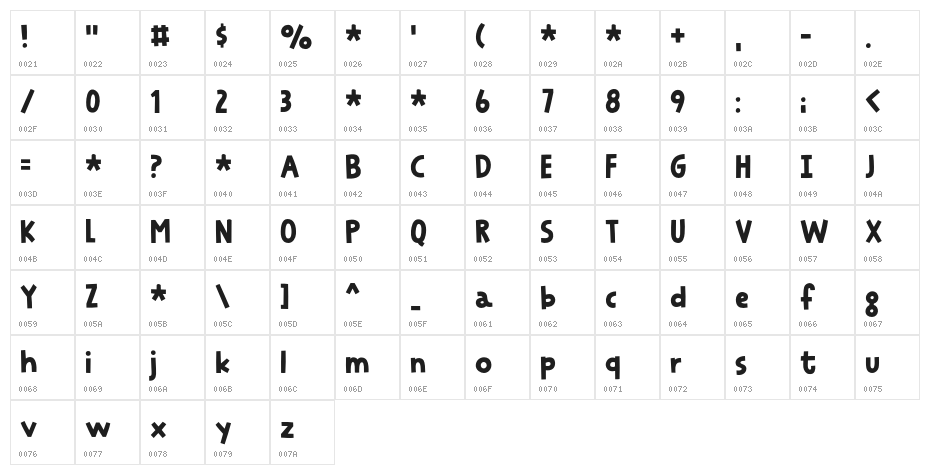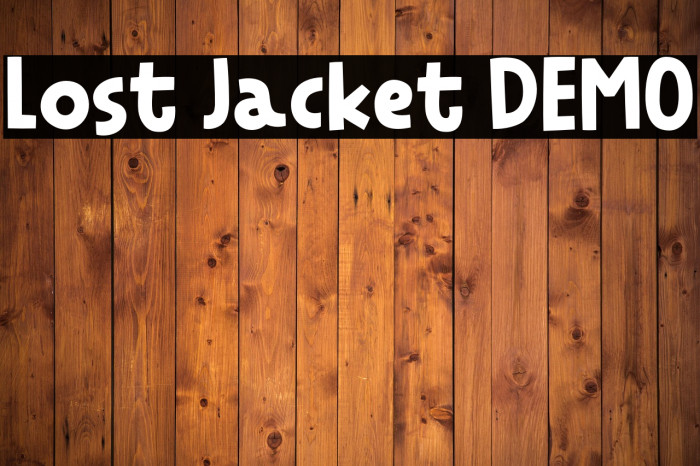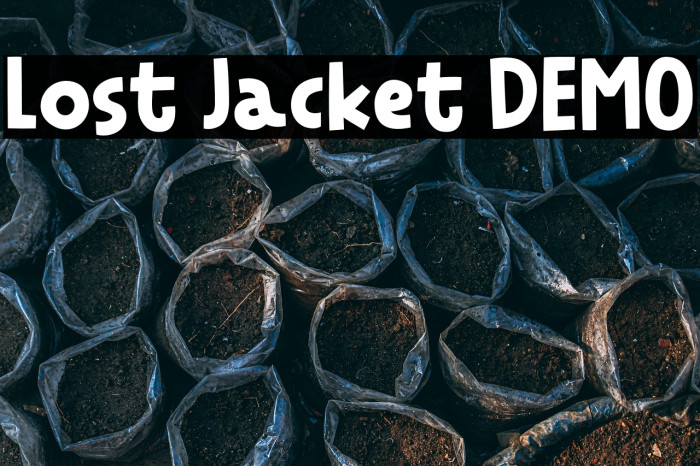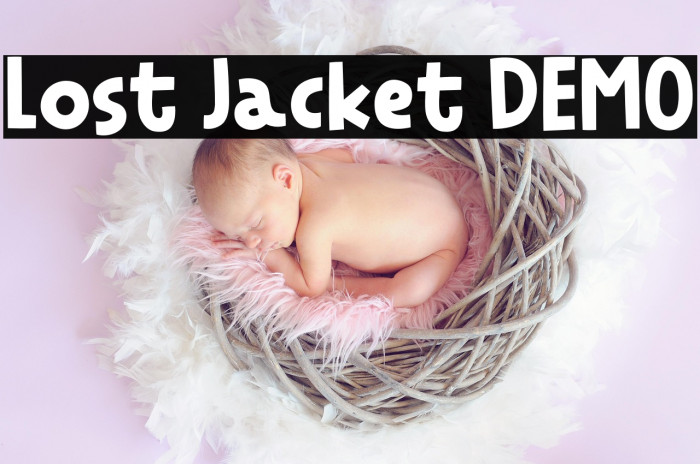
Lost Jacket DEMO Font
| Stile generale | Playful, Whimsical |
| Progetti proposti | Ideal for children's books, comic strips, playful branding, and creative posters. |